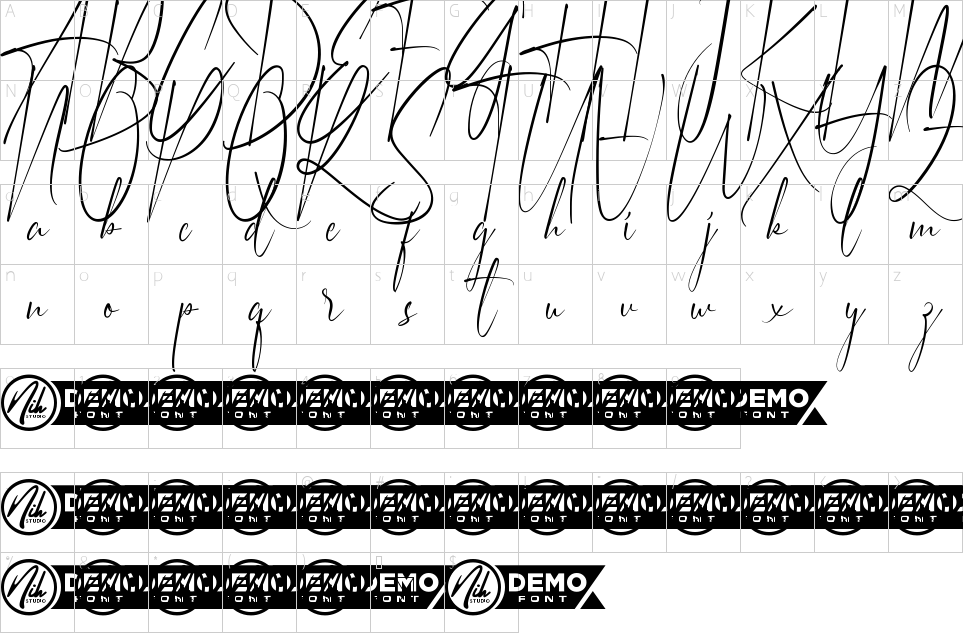
Descubra a beleza do Jangan Pergi Font para seus projetos digitais gratuitamente com esta descarga conveniente. Desenhada pelo nihstudio, essa font é uma escolha perfeita para os designers que procuram um estilo elegante e versátil. Com seu design cuidadoso e levemente romântico, Jangan Pergi oferece linhas suaves e legíveis, ideal para criar texto atraente em qualquer aplicativo de Windows ou Mac. Seja para o site da sua empresa, o layout de uma newsletter ou até mesmo para aquele projeto personalizado que está te encher de orgulho, Jangan Pergi pode ajudá-lo a dar um toque especial à sua escrita digital. Com seu design único e facilmente acessível por meio desta página, você pode ter essa beleza gráfica sem gastar uma centavos extra. Descubra agora mesmo a magia do Jangan Pergi Font para seus projetos digitais!